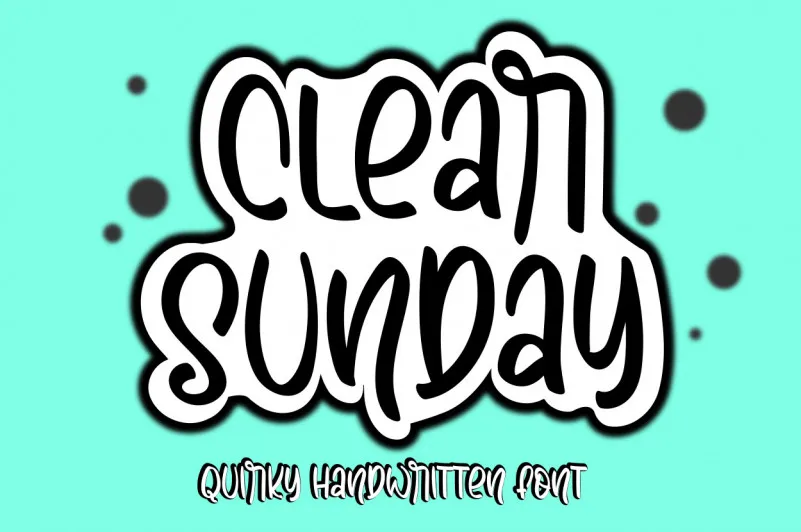
Clear Sunday Font – Download Grátis
Descubra a arte delicada e fluida da Clear Sunday Font no designer sugiharto1790. Esta fonte escrita à mão é mais do que uma simpleza visual; ela transmite tranquilidade e simplicidade, criando um ambiente ideal para textos de qualidade em ambientes profissionais ou pessoais. Seja você um freelancer desenhando suas criações, um designer de sites buscando aperfeiçoar sua interface com a letra perfeitamente elegante da Clear Sunday Font, ou simplesmente alguém adorando criar design gráfico no seu tempo livre, esta fonte oferece uma mistura harmônica e suave que complementa qualquer projeto. Com uma estrutura fluida e um estilo autêntico à mão, a Clear Sunday traz vida aos seus projetos. Seja para textos de blog, letras em banners publicitários ou até mesmo texturas minimalistas em artigos de design – sua fórmula perfeita de sofisticação e elegância certamente impressionará. Ainda não experimentou o poder da Clear Sunday Font? Instale-a agora e mergulhe nesse mundo de texto. Garanta que você está confortável com todas as regras do uso do produto ao instalar ou utilizar esta fonte, e explore a variedade criativa e calma que ela tem para oferecer.